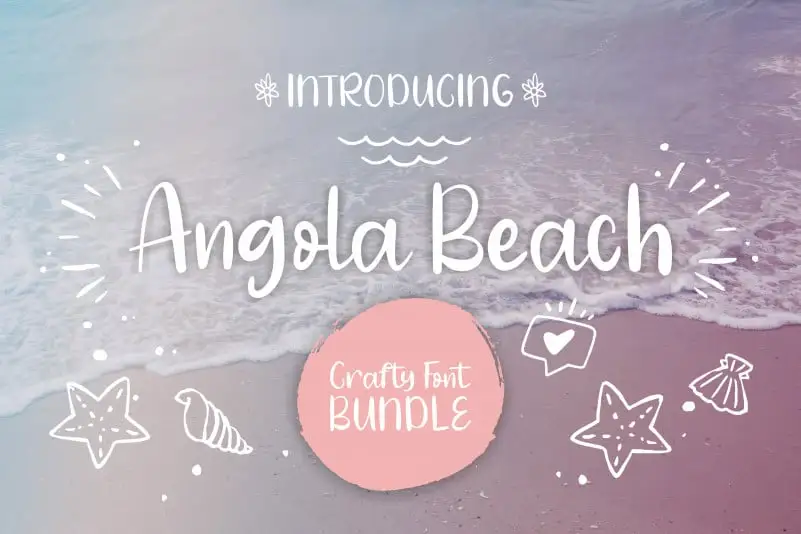
Angola Beach Script Font – Download Grátis
A Angola Beach Script Font é uma elegante tipografia à mão escrita que transmite sentimentos suaves e agradáveis. Desenhada com um estilo natural e único, ela se destaca para uma variedade de projetos design. Seu charme encantador e peculiar tornam-se perfeitos para qualquer visual gráfico imaginado por você. A única limitação é sua imaginação. Engane-se, faça o seu e torne a Angola Beach Script Font parte inegável da sua paleta de fontes.